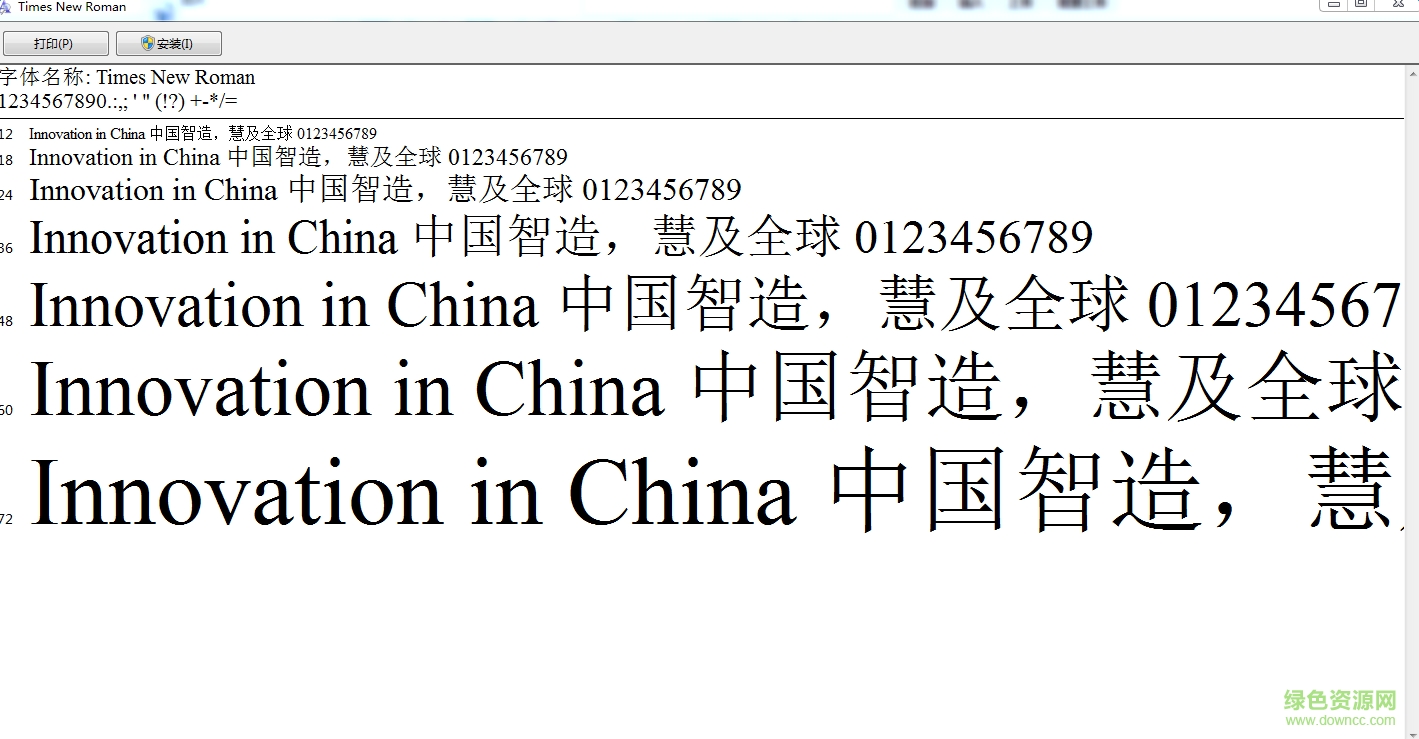
times new roman是什么字体?new times roman字体是生活中最常见的一款英文衬线字体,在报告、公文、广告、荧幕显示、图书、杂志等领域都可见这款字体,需要的朋友来绿色资源网免费下载吧!
Times New Roman字体介绍
Times New Roman是一种广泛使用的字体,属于过渡衬线体。截线如被切割般平整、纤细、末端矩形,字母宽度差别较小,显得四平八稳,应用范围广泛。Times NewRoman笔画比Garamond稍粗,粗细变化也较Garamond小,Times NewRoman显示小字时易读性仍然很高,作为标题就不那么醒目了。